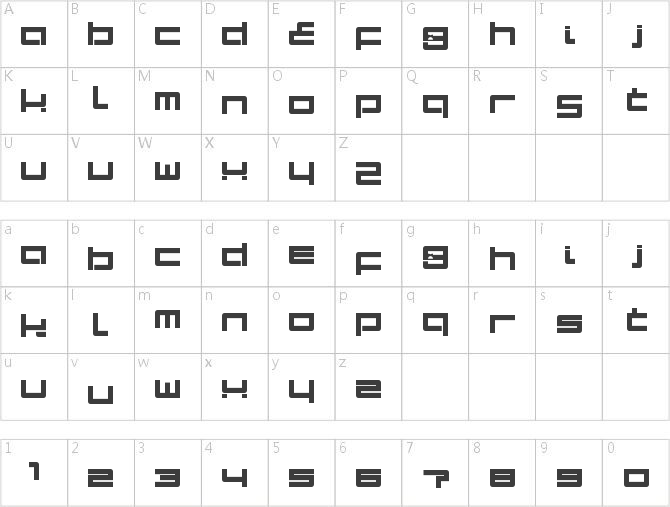
字體名稱: Proto-L
Proto-LDR-Regular
Proto-LDR-Regular介紹
Proto-LDR-Regular字體字庫是一款讓人賞心悅目、百看不厭的英文字體,適合各類廣告和產(chǎn)品包裝設(shè)計應用,字體大小0.01MB,格式為ttf字體,上傳用戶是錦程正陽,作者/版權(quán)方為未知